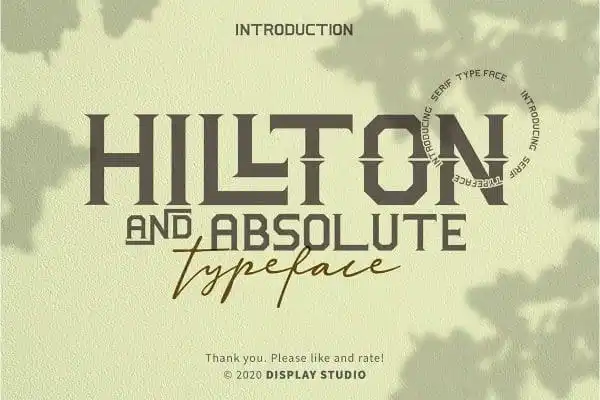
Hillton And Absolute Display Font – Download Grátis
A fonte Hillton And Absolute Display é uma escolha perfeita para quem busca uma qualidade premium e um estilo luxuoso que destaca seu trabalho. Criada com cuidado, esta fonte combina a sofisticação de ligaturas únicas que fazem dela algo singular em meio às serifas tradicionais. Ideal tanto para logotipos de marca quanto para cartões de convite ou cartas de feliz aniversário, esta tipografia também é perfeita para qualquer projeto. Com uma característica multilíngue e variações de estilo, Hillton And Absolute Display não apenas complementa o aspecto estético do seu trabalho, mas a fortalece ainda mais. Sempre idealizada para quem valoriza qualidade e design, esta fonte é uma opção criativa que certamente enriquecerá seu próximo projeto visual.